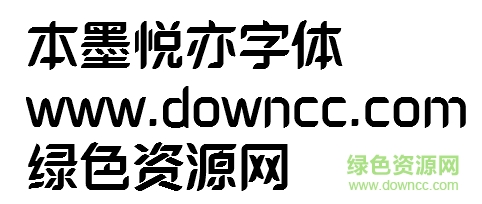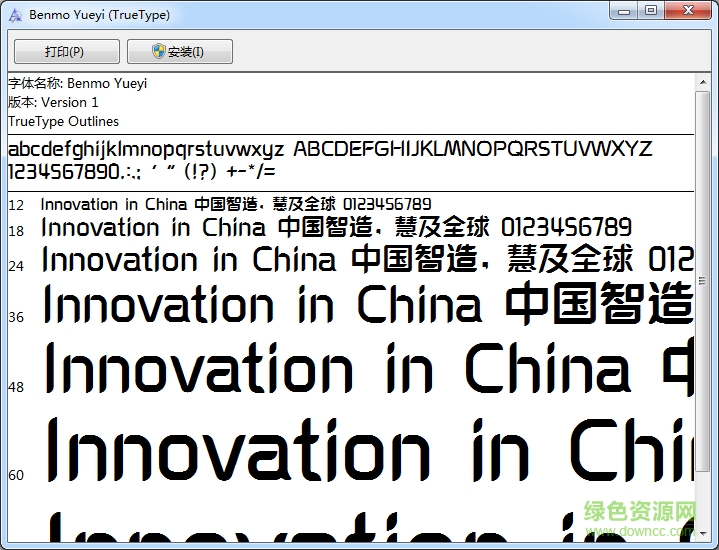
本墨悅亦ttf是一款端正秀美的藝術(shù)字體,字體圓潤也有棱角,造型大方簡潔,讓你的設(shè)計(jì)更有獨(dú)特魅力,歡迎大家在綠色資源網(wǎng)下載本墨悅亦正版字體!
本字庫中文以國家GB2312-80標(biāo)準(zhǔn)設(shè)計(jì)制作,中文字?jǐn)?shù)6763個(gè),另包含ASCII常用字符150個(gè)。
本墨悅亦字體寬綽秀美外似柔潤而內(nèi)實(shí)堅(jiān)強(qiáng),形體端秀而骨架勁挺,識(shí)別性強(qiáng),端正大方,整體風(fēng)格出色。可以廣泛應(yīng)用于廣告設(shè)計(jì)、宣傳海報(bào)、ppt、影視制作以及任何使用文字的領(lǐng)域